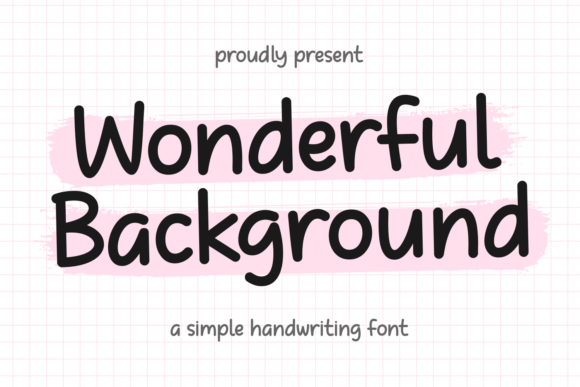
Wonderful Background
Se você está procurando ativos de alta qualidade como Wonderful Background, este pacote premium é uma escolha fantástica para seus projetos criativos.
Trabalhado com precisão, Wonderful Background fornece vetores limpos, tipografia suave e uma licença comercial para sua tranquilidade.